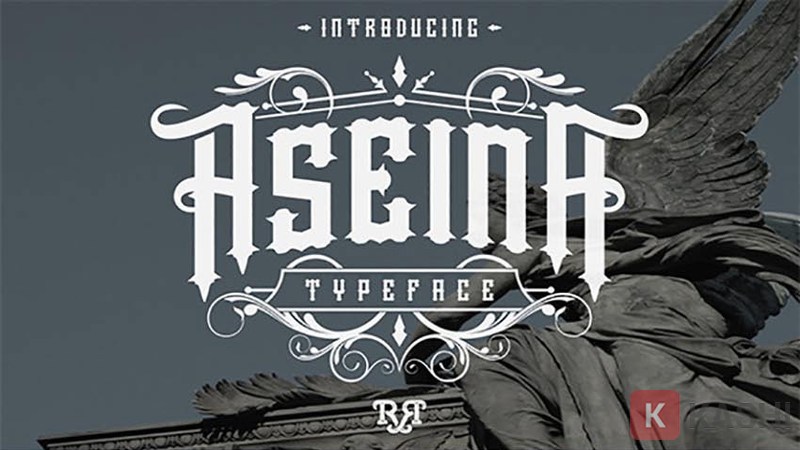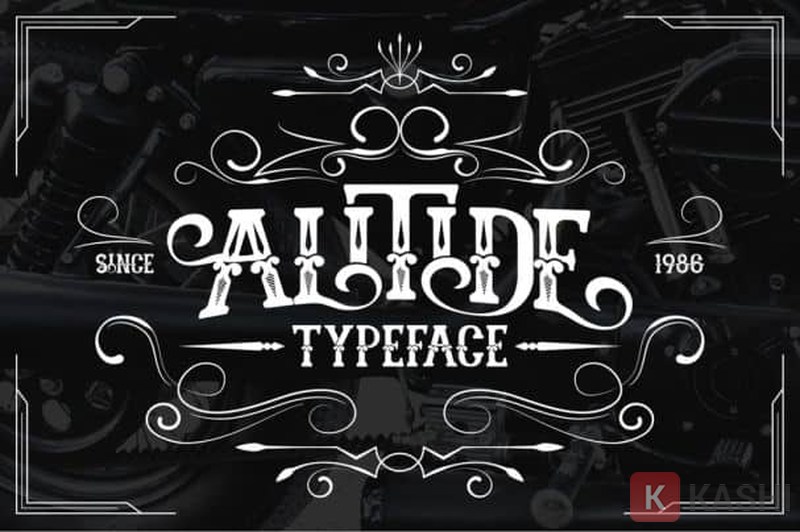
15+ Font Chữ Xăm Tên Đẹp và Ấn Tượng Nhất 2025
Xu hướng xăm chữ ngày càng được ưa chuộng bởi giới trẻ, không chỉ thể hiện cá tính mà còn mang ý nghĩa riêng. Bài viết này tổng hợp hơn 15 font chữ xăm tên đẹp, độc đáo và ấn tượng nhất năm 2025, giúp bạn tìm kiếm nguồn cảm hứng cho hình xăm tiếp theo.
Xăm hình nghệ thuật đã trở thành một hình thức thể hiện bản thân phổ biến, cho phép giới trẻ lưu giữ kỷ niệm và thể hiện cá tính riêng. Xăm chữ, một nhánh của nghệ thuật xăm hình, sử dụng các kiểu chữ cách điệu, kết hợp với họa tiết hoa lá, tạo nên những hình xăm độc đáo và ý nghĩa.
Xăm Nghệ thuật: Khái niệm và Phân loại
Xăm Nghệ thuật là gì?
Xăm hình nghệ thuật là việc sử dụng mực để tạo hình trên da, mang tính thẩm mỹ hoặc lưu giữ dấu ấn cá nhân. Khác với phương pháp truyền thống, công nghệ hiện đại cho phép tạo ra những hình xăm 3D phức tạp, đa dạng về mẫu mã và hình thức.
Hình Xăm Chữ là gì?
Hình xăm chữ là một loại hình xăm sử dụng chữ cái, được cách điệu và kết hợp với các họa tiết khác nhau. Kích thước và kiểu dáng của hình xăm chữ phụ thuộc vào sở thích cá nhân.
Tổng hợp 15+ Font Chữ Xăm Đẹp và Độc Đáo 2025
Từ chữ thư pháp đến font chữ máy đánh chữ, hình xăm chữ mang đến vẻ đẹp tinh tế và cá tính. Dưới đây là một số font chữ xăm nổi bật nhất năm 2025:
1. Aseina Typeface: Phong Cách Vintage
Aseina Typeface là sự kết hợp hoàn hảo giữa chữ cái, số và glyph, mang đến vẻ đẹp cổ điển, thanh lịch và sang trọng. Font chữ này đặc biệt phù hợp với những ai yêu thích phong cách vintage.
Font Aseina Typeface
2. November Script Font: Nét Đẹp Thủ Công
November Script Font được thiết kế thủ công và số hóa, tạo nên nét chữ thư pháp mềm mại, uyển chuyển. Bộ font bao gồm chữ cái, số và các dải buộc, cho phép tạo ra những hình xăm phức tạp và tinh tế.
Font November script font khi xăm trên da
3. Alitide Typeface: Cảm Hứng Phương Tây Cổ Xưa
Lấy cảm hứng từ thiết kế phương Tây cổ xưa, Alitide Typeface mang đến nét uốn lượn hiện đại, phù hợp với những ai yêu thích sự sáng tạo.
Alitide font
4. Brushgyo Typeface: Thiết Kế Script Hiện Đại
Brushgyo Typeface là font chữ viết tay hiện đại, phù hợp cho cả in ấn và xăm nghệ thuật. Bộ font bao gồm chữ cái, số và hỗ trợ đa ngôn ngữ.
brushgyo font
5. Stay High Typeface: Phong Cách Graffiti
Stay High Typeface lấy cảm hứng từ đường phố, với những đường cong tự do, phóng khoáng. Đây là lựa chọn hoàn hảo cho những ai yêu thích phong cách graffiti.
hình xăm theo phong cách graffiti
6. Sekatoan: Phong Cách Độc Đáo
Với phong cách gọn gàng, đường nét in đậm và đổ bóng, Sekatoan mang đến sự nổi bật cho hình xăm.
7. Bekelakar Typeface: Thiết Kế Lạnh Lùng
Bekelakar Typeface là lựa chọn phù hợp cho những ai yêu thích phong cách lạnh lùng, rùng rợn. Bộ font bao gồm chữ thường, chữ in hoa, số và dấu câu.
8. Jimmy Font Duo: Xu Hướng Vintage Hiện Đại